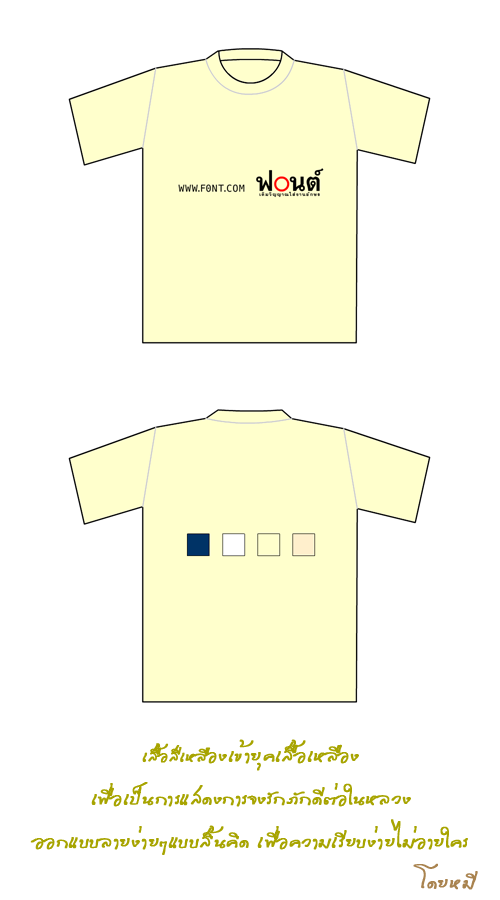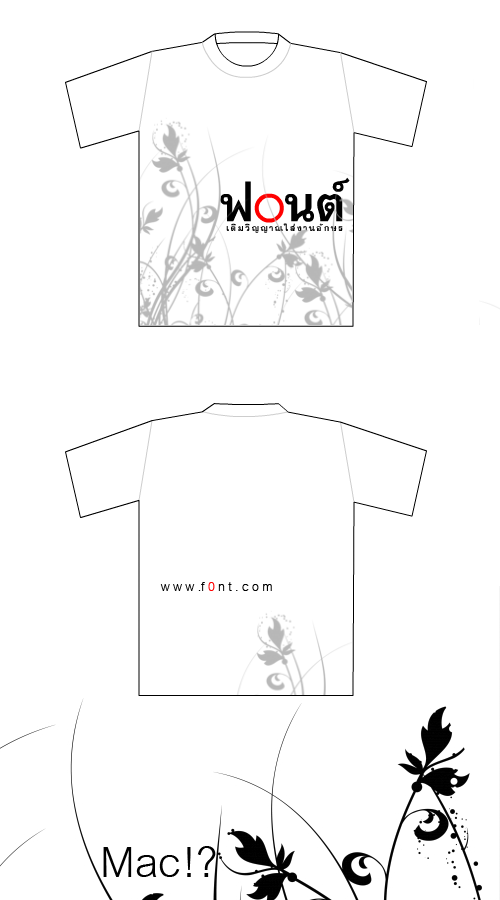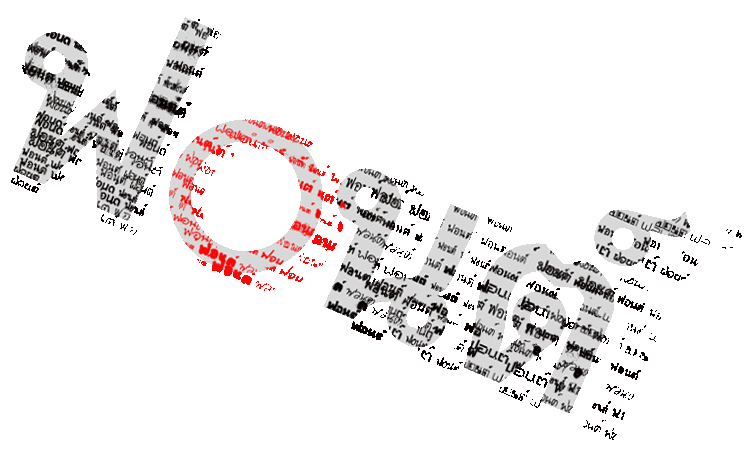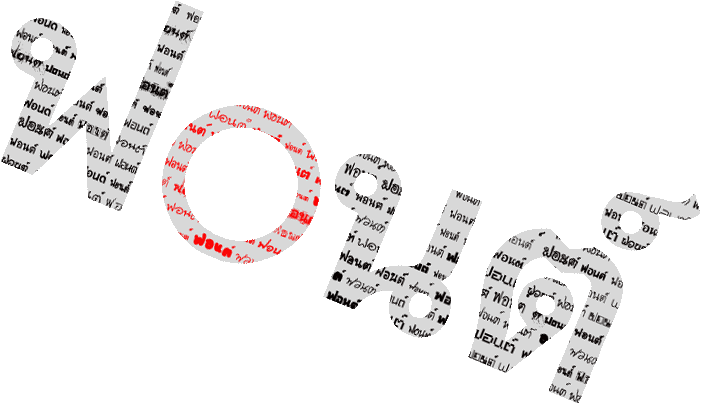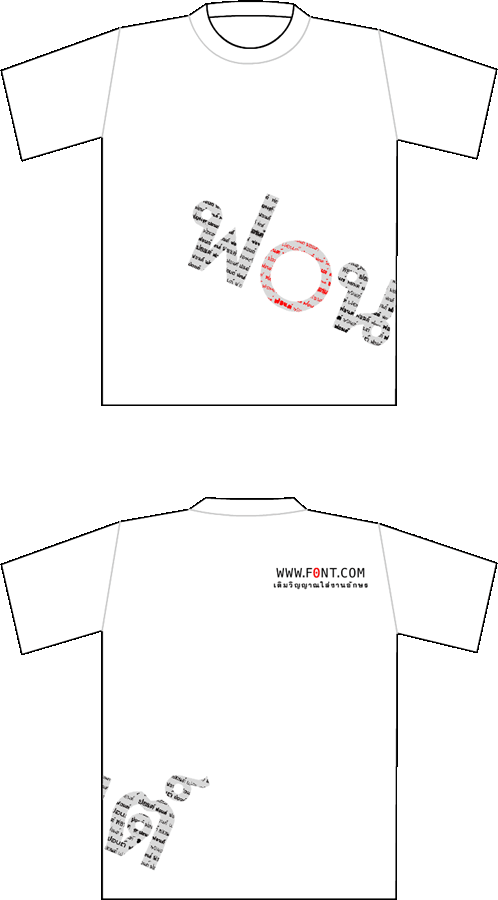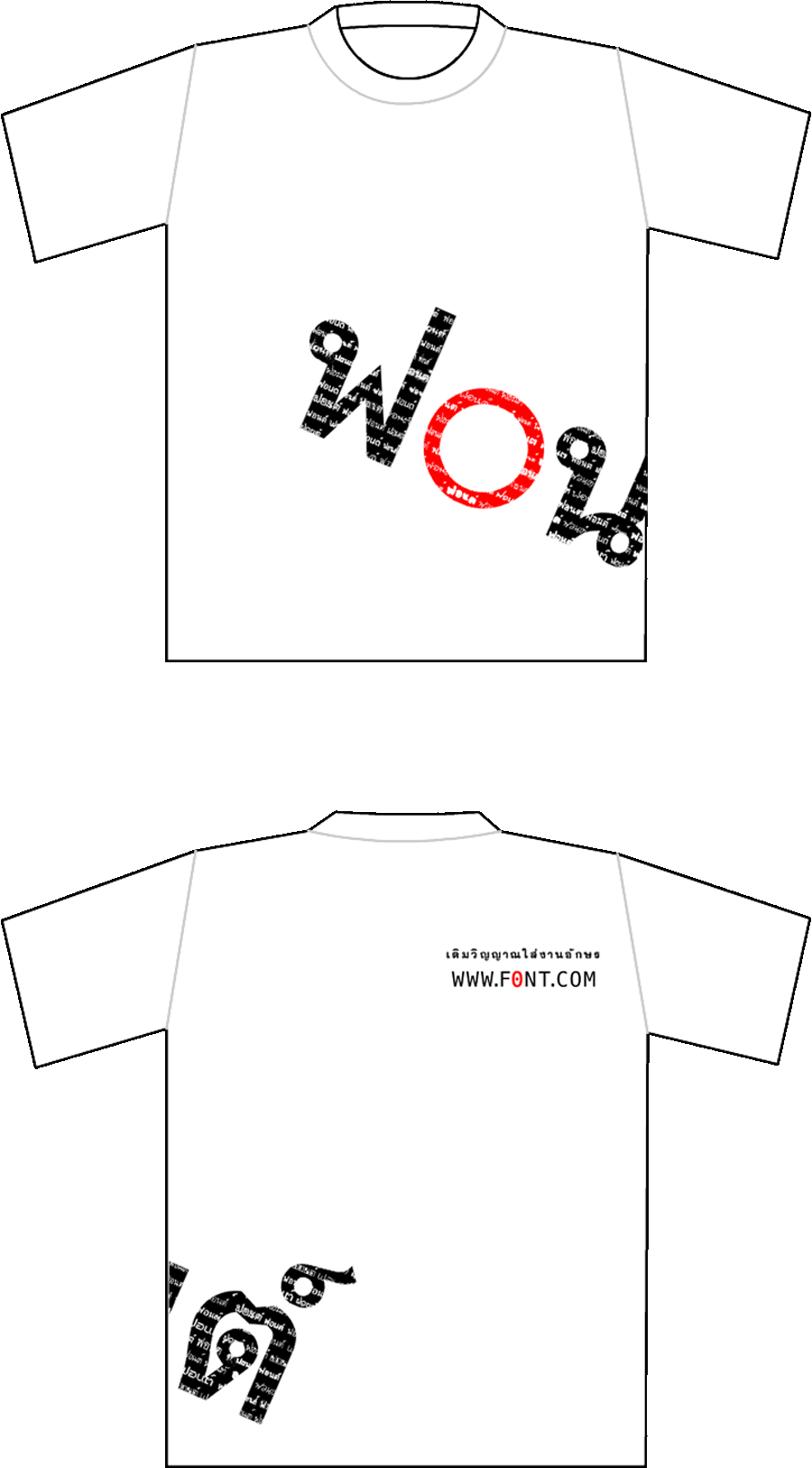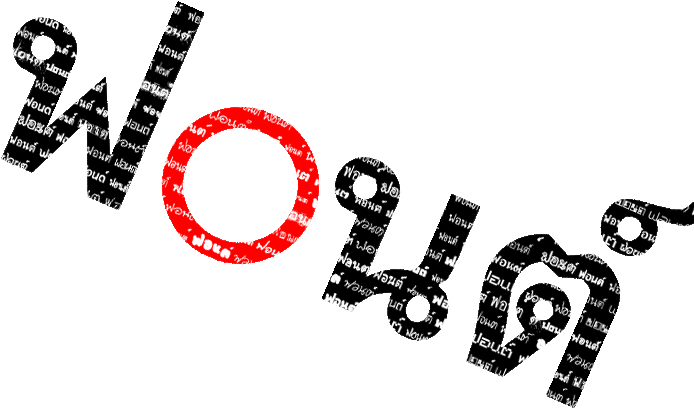
FC7 : เสื้อฟ๐นต์ ภาคสooง
ทนๆ ดูไปเถอะนะครับ สี่ชุดนี้ก็แนวเีดียวกันต่างกันที่การนำเสนอรูปแบบคำว่าฟอนต์ แนวคิดคือตั้งใจเสนอให้เห็นความหลากหลายของฟอนต์ของแต่ละคน ว่า เออ แบบอักษรไทยมันไม่ได้มีแค่อังสนา วงการนี้ก็มีฟันเฟืองเล็กๆ มากมายที่ทำให้ฝันเฟื่องนี้ขยับเขยื้อน และเป็นจริง
เอาแบบเก่ามาแก้ค่ะ
เพราะพี่แอนบอกว่า มันเปลืองบล็อก  :39:
เน้นสีขาวดำ(เพราะกำลังอินเทรน)
โดดเด่นด้วยลายเส้นการ์ตูน และดีไซน์ที่ไม่เหมือนใคร
พร้อมมุกโดนใน
ใส่แล้วใครๆก็ต้องมอง  :12:
อีกแบบค่ะ
เป็นเสื้อขาว
ลายหัวใจ ซึ่งอยู่ตรงตำแหน่งหัวใจจริงๆ
หัวใจพูดคำว่าฟอนต์
ด้านหลังเป็นสัญลักษณ์ประจำตัวพี่แอน
และมีurlของเว็บนี้ด้วย
ทำมาเล่นๆคับ  :22:
แบบแรกมี 2  ลาย ของผู้ชายกับผู้หญิงนะครับ ห่วยมาก!! :08:
อันที่ 2 ก็ง่ายๆ ครับ  :42:
แถมอีกอันละกันครับ
ข้างหลังน่าจะมีเพิ่มคำว่า
1 ในผู้กินกับ
ที่ไม่ได้รู้จักกับผู้กำกับภาพยนต์
เรื่องฟ0นต์ฉัน